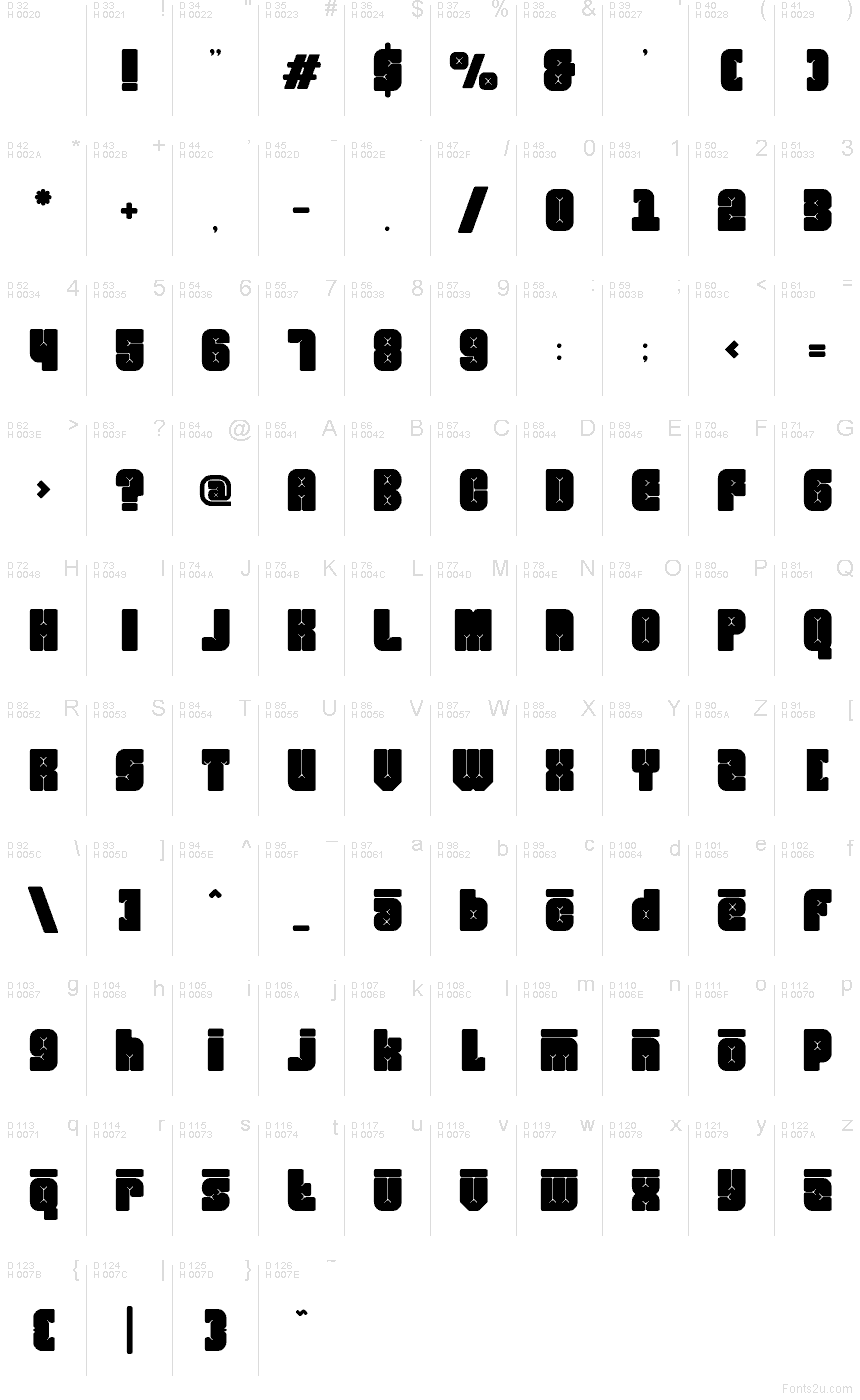
Friez od Putracetol Studio je bezplatné groovy písmo typu display, vytvořené z podsaditých, zaoblených bloků, které se v řádku rozprostírají jako měkké modulární dlaždice. Tato nízká, příjemná silueta je zostřena malými zářezy a zlomy připomínajícími jiskry, díky čemuž znaky nepůsobí tupě ani genericky.
Hudební plakáty, streetwearové grafiky, obaly alb, návrhy nálepek a titulky na obalech – tam všude dává Friez smysl, protože široké tvary vytvářejí silnou grafickou hmotu ještě předtím, než se projeví dekorativní řezy. Písmo skvěle poslouží také v brandingu kaváren nebo jako nadpisy na sociálních sítích, kde krátké slovo vyžaduje výraznou, stylizovanou přítomnost namísto obyčejného retro vzhledu.